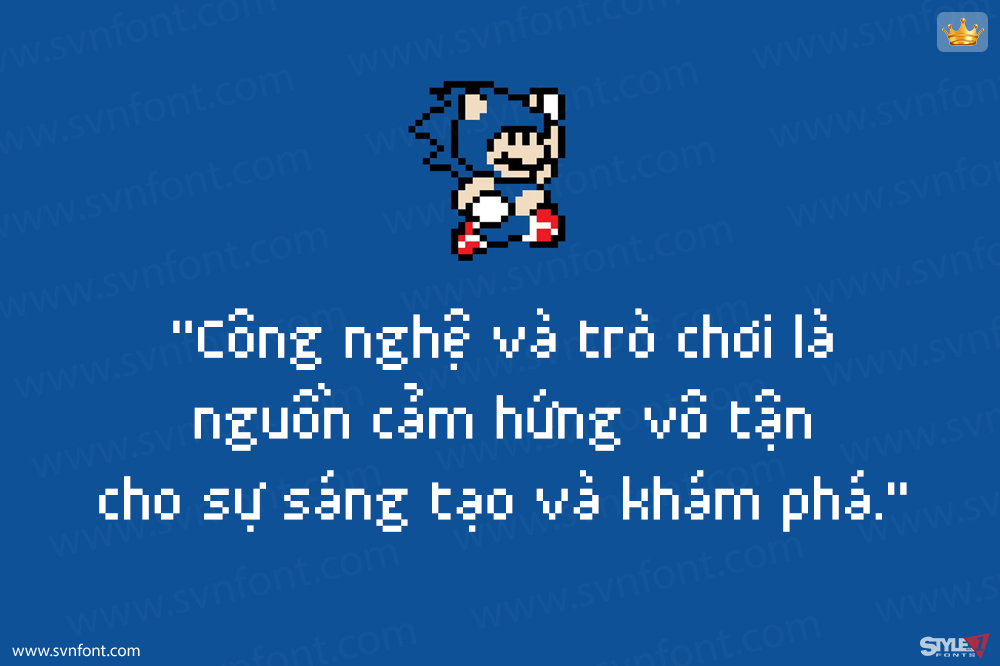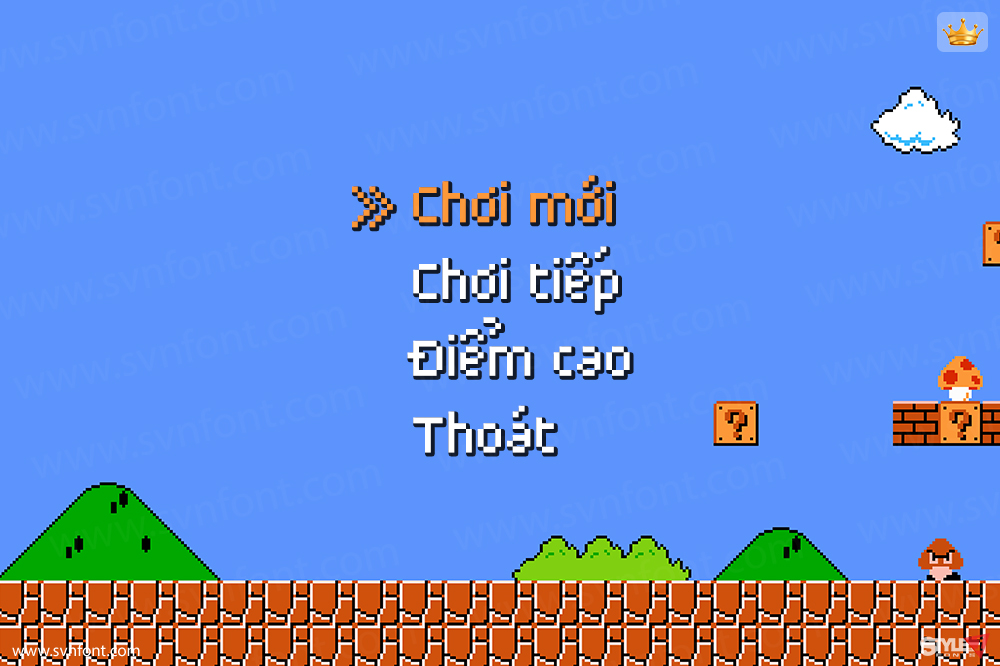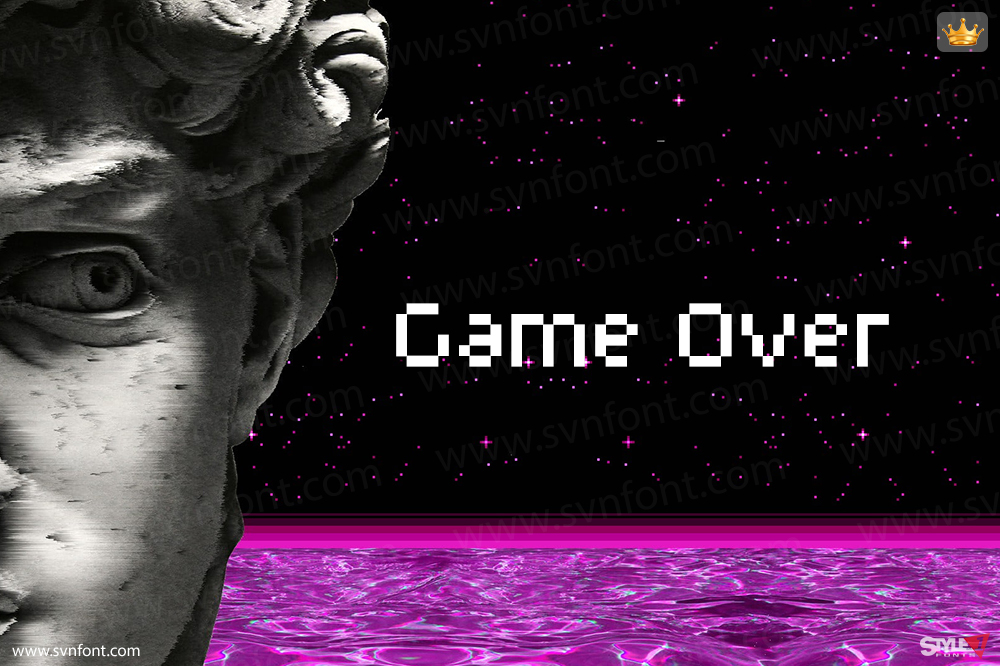
Pixer là một phông chữ pixel hiển thị lấy cảm hứng từ thẩm mỹ kỹ thuật số sơ khai của những năm 70 – thời kỳ hoàng kim của trò chơi điện tử arcade và đặc biệt là trò chơi Space Invaders khét tiếng. Được xây dựng hoàn toàn từ các điểm ảnh, kiểu chữ này tuân theo công nghệ phông chữ bitmap tiên phong cho màn hình có độ phân giải thấp, nhưng chúng tôi đã làm cho nó hoạt động hoàn hảo trên cả màn hình chất lượng thấp và cao. Fontfabric mang đến Pixer miễn phí để làm phấn khích mọi game thủ tự xưng! Không có cạm bẫy bí mật nào cả! Tất nhiên là vậy, để bạn có thể tiết kiệm tiền cho nhiều xu arcade hơn…
Nhà thiết kế: Nikolay Petroussenko
Nhà phát hành: Fontfabric